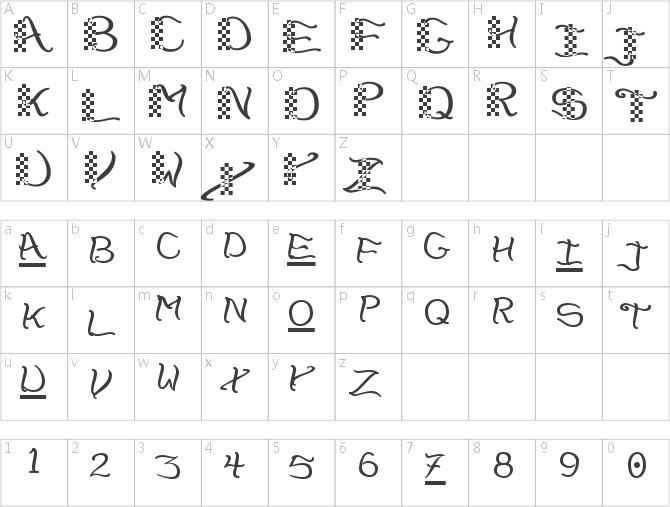
Chech___ 詳情頁(yè)
Chech___字體字庫(kù)是一款讓人賞心悅目、百看不厭的英文字體,適合各類(lèi)廣告和產(chǎn)品包裝設(shè)計(jì)應(yīng)用,字體大小0.03MB,格式為ttf字體,上傳用戶(hù)是shiqiuping,作者/版權(quán)方為未知